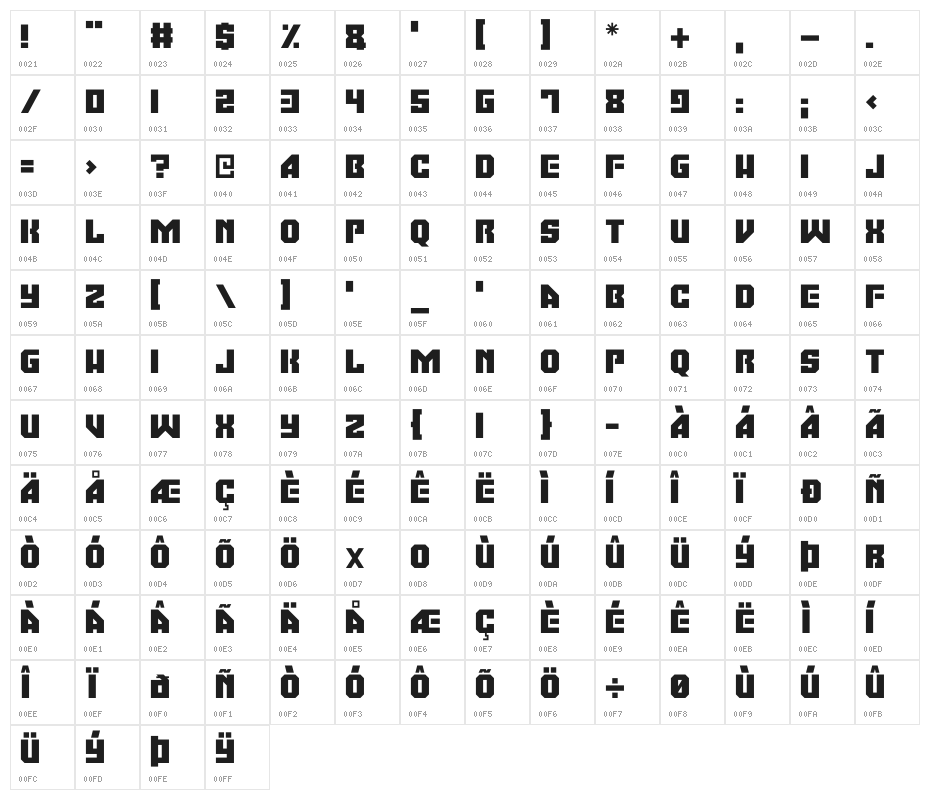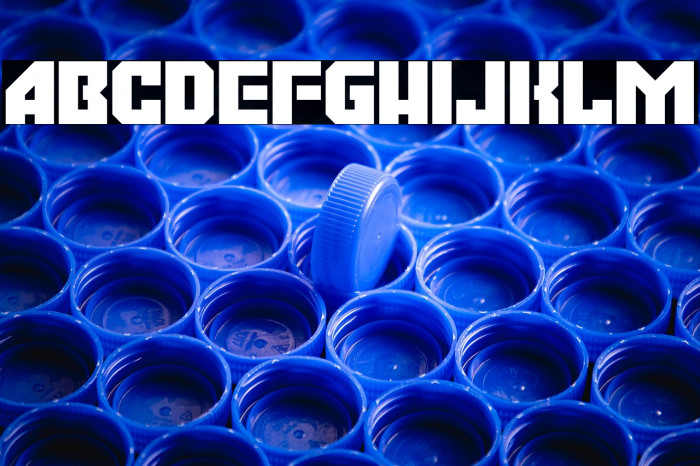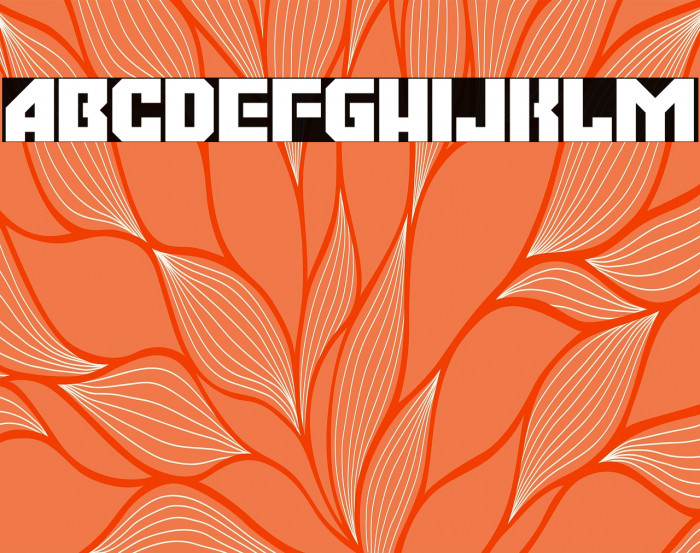
Moonbase Omega Font
| Style général | Futuristic, Industrial |
| Projets proposés | Ideal for sci-fi themed designs, video game titles, posters, and branding that requires a strong, modern look. |
Moonbase Omega